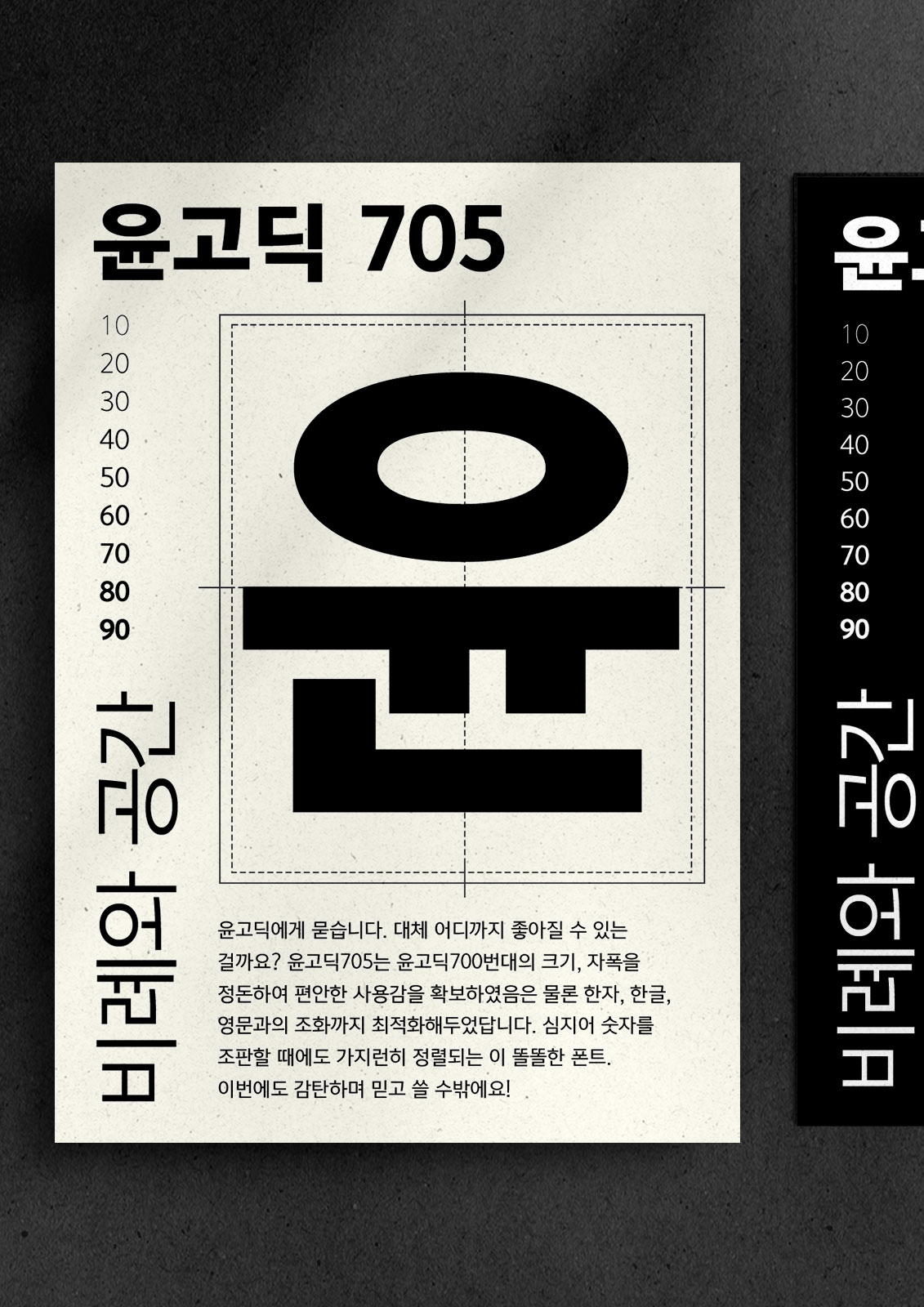
윤고딕705
Yoon 윤고딕705
윤고딕에게 묻습니다. 대체 어디까지 좋아질 수 있는 걸까요? 윤고딕705는 윤고딕700번대의 크기, 자폭을 정돈하여 편안한 사용감을 확보하였음은 물론 한자, 한글, 영문과의 조화까지 최적화 해두었답니다. 심지어 숫자를 조판할 때도 가지런히 정렬되는 이 똘똘한 폰트. 이번에도 감탄하며 믿고 쓸 수밖에요!